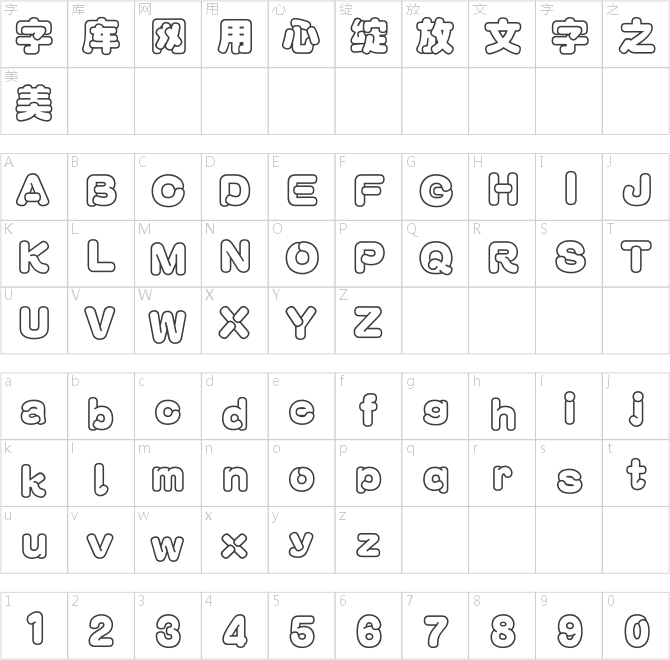
文鼎彩云简繁_U
文鼎彩云简繁_U介绍
和无『_u』的版本相比更换了西文。20220120更新Power TrueType Version 5.5版:添加日语当用汉字。一共16721个汉字。20220204更新:修正「爲」「僞」分别显示为「為」「偽」的错误。
文鼎彩云简繁_U字体文鼎空叠圆简繁_U字库是一款让人赏心悦目、百看不厌的中文字体,适合各类广告和产品包装设计应用,字体大小18.5MB,格式为ttf字体,上传用户是伊宁,作者/版权方为文鼎字库